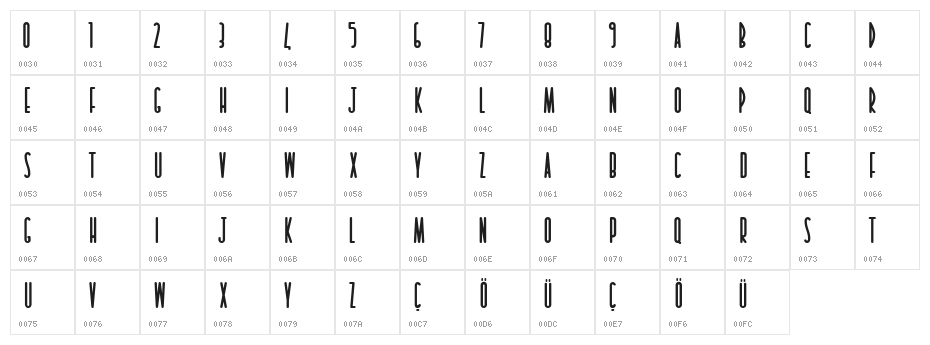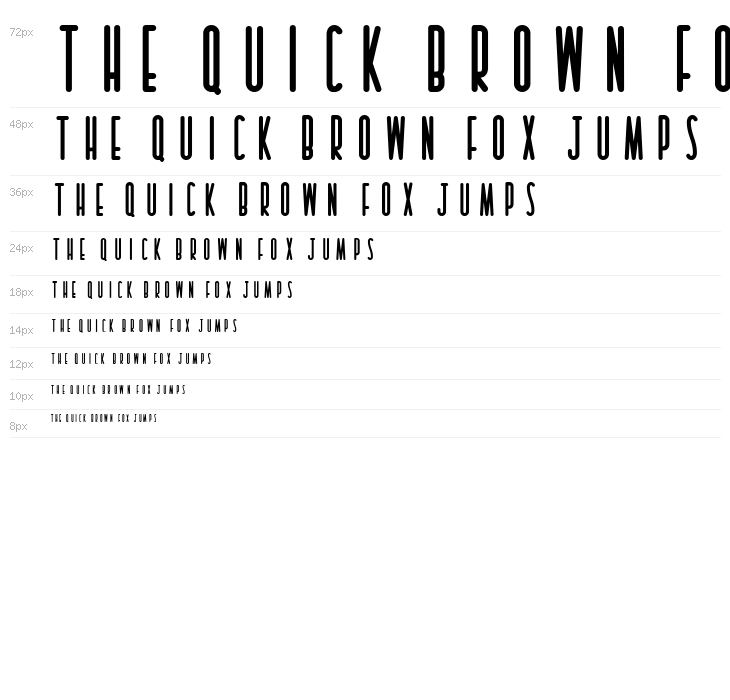
Bodrum Font
| Vorgeschlagene Projekte | Ideal for branding projects, poster designs, and modern editorial layouts where a distinctive and stylish typeface is needed. |